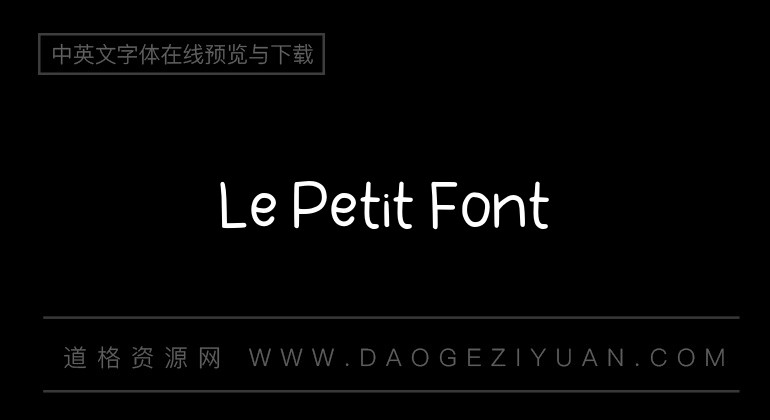
Le Petit Font
Le Petit Font 是一种手写风格的英文字体,其特点是线条柔和、优雅,字母间距恰到好处,非常适合用于设计卡片、海报、宣传册等文化创意领域。这种字体有多种风格和变体可供选择,包括常规、粗体、斜体和粗斜体等,使得设计师可以根据具体要求选择最合适的字体风格。Le Petit Font 可以在多种设计软件中使用,如 Adobe Photoshop、Illustrator、InDesign 等,也可以在网站设计中使用。
Le Petit Font是一款非常不错的手写艺术字体,具有很好的视觉感,适合于文化类的宣传设计、商业类品牌的广告和产品包装设计以及个性化文字排版等较多场景。